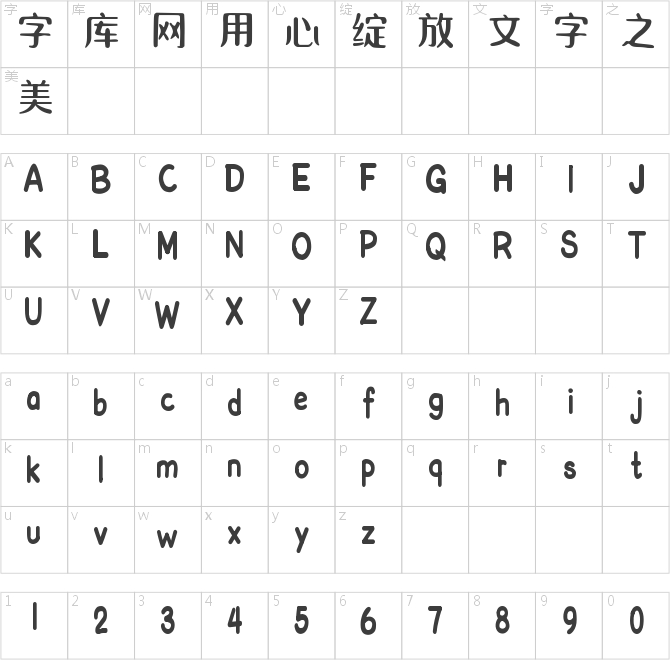
文道招財(cái)進(jìn)寶
文道招財(cái)進(jìn)寶字體招財(cái)進(jìn)寶字庫是一款讓人賞心悅目、百看不厭的中文字體,適合各類廣告和產(chǎn)品包裝設(shè)計(jì)應(yīng)用,字體大小4.27MB,格式為ttf字體,上傳用戶是文道字庫,作者/版權(quán)方為文道字庫